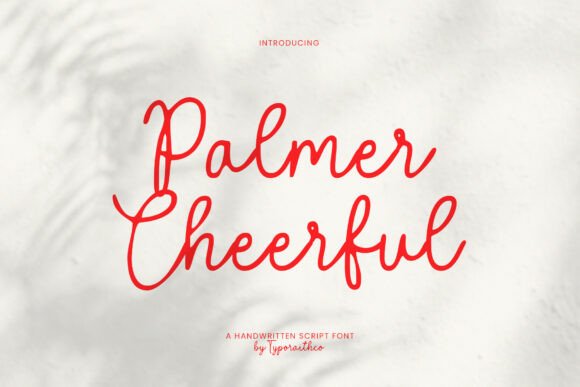
Palmer Cheerful
適切なデザイン要素を見つけるのは難しい場合がありますが、Palmer Cheerfulは作品を即座に引き立てる優れたコレクションを提供します。
POD(オンデマンド印刷)製品、結婚式の招待状、またはソーシャルメディアのグラフィックを作成している場合でも、Palmer Cheerfulは理想的です。